文字だけで怖い!ホラー・恐怖・オカルト系のフリーフォント35選
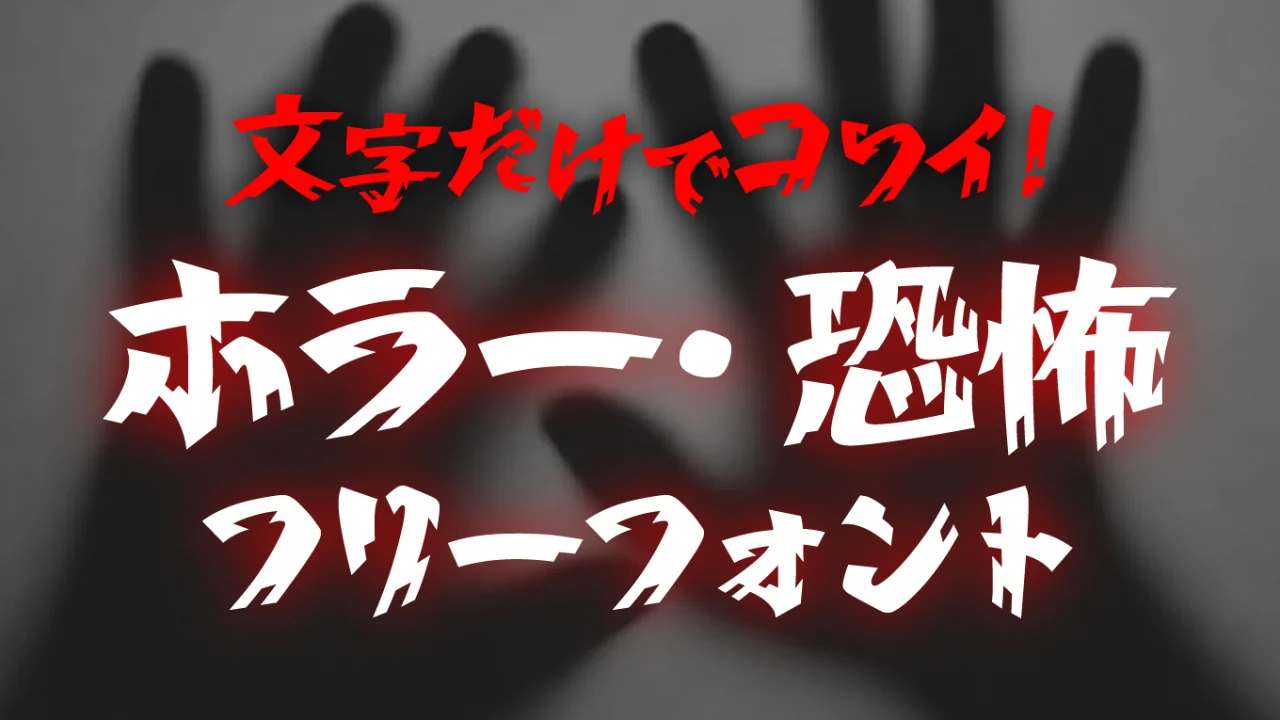
デザインでホラーや恐怖、オカルト、不気味さ、悪人らしさ、精神的な動揺や疲労感などを表現したいとき、フォントの印象で文字を選ぶ場面は意外と多いものです。文字は情報を伝えるだけでなく、見る人に感情や空気感を伝える大切なデザイン要素でもあります。
同じ言葉でも、フォントが変わるだけで「不気味さ」や「狂気」「不安感」「違和感」といった印象は大きく変化します。かすれた文字や歪んだ文字、崩れたような字形などを使うことで、視覚的に強いインパクトを与えることもできます。
今回は、ホラー・恐怖・オカルト系の演出にぴったりな日本語フリーフォントをご紹介します。恐怖演出はもちろん、悪役のセリフ、サスペンス作品、疲労感や混乱状態を表現したい場面、動画のテロップやアイキャッチなどにも活用できます。
文字だけでも十分に“怖い”。そんなインパクト抜群のホラー・恐怖系フリーフォントをぜひチェックしてみてください。今回は「不気味・不穏・サイコ」「和風ホラー・怪談」「お化け屋敷・ゾンビホラー」といったカテゴリごとにご紹介します。
ホラー・恐怖系のフリーフォントのまとめ
以下のサンプル画像は、本記事で紹介しているフォントの一部です。かすれや歪み、不規則な輪郭、崩れた字形など、それぞれ異なるアプローチで“恐怖”や“不気味さ”を表現しており、文字だけでも強いホラー感が伝わるデザインとなっています。
ホラー作品やオカルト系デザインはもちろん、不安感や狂気、違和感を演出したい場面でも活躍するフォントばかりなので、ぜひデザイン制作やアイキャッチ、動画テロップなどに取り入れてみてください。
不気味・不穏・サイコにおすすめホラーフォント
じわじわと不安を煽るような演出や、どこか異常さを感じさせるデザインを作りたいときは、フォント選びがとても重要です。文字の歪みや不揃いさ、独特な違和感をもつフォントを使うことで、サイコホラーや不気味な世界観をよりリアルに表現できます。まずは、不穏さや狂気を感じさせるホラーフォントを紹介します。
コミック古印体
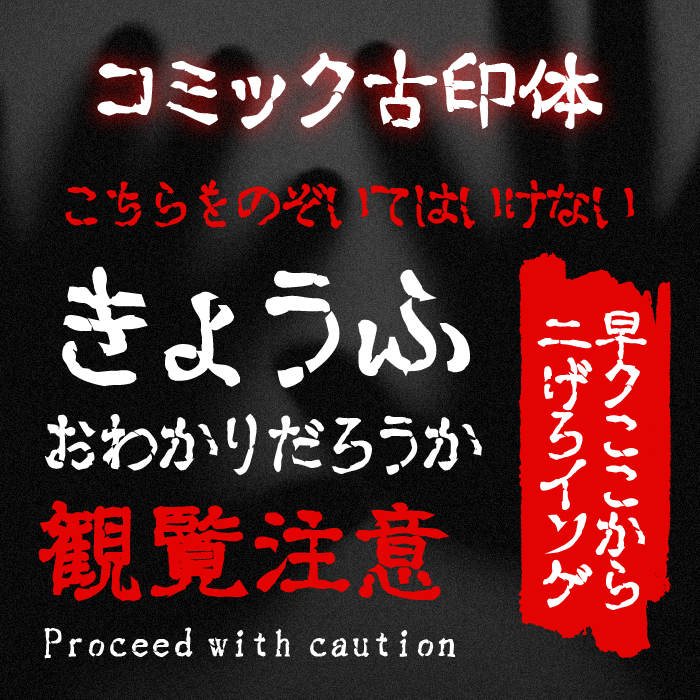
| ホラー・恐怖度 | ★★★★★ |
| おすすめのシーン | 怪談、呪いのメッセージ、警告表示、都市伝説、サスペンス演出 |
コミック古印体は、かすれた質感と不規則な線の揺らぎが特徴的なフォントです。どこか古びた印象や不安定さを感じさせるデザインで、文章そのものに不気味な空気感を与えられます。ホラー作品のタイトルや警告文にもぴったりなフォントです。
漫画の吹き出しやセリフなどにもぴったりです。
イバラ字
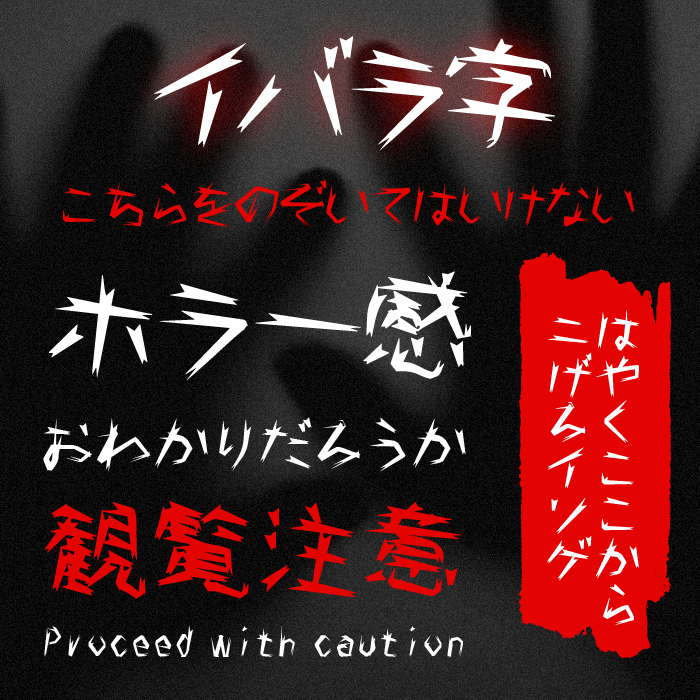
| ホラー・恐怖度 | ★★★★☆ |
| おすすめのシーン | 襲撃シーン、狂気表現、パニック演出、ホラーゲーム、危険警告 |
イバラ字は、鋭く尖ったエッジと引き裂かれたような独特の造形が印象的なフォントです。攻撃的で不安を煽るデザインになっており、視覚的に強い恐怖感や異常性を演出できます。ホラーゲームやパニック演出にも相性が良いフォントです。
異國ひらがな
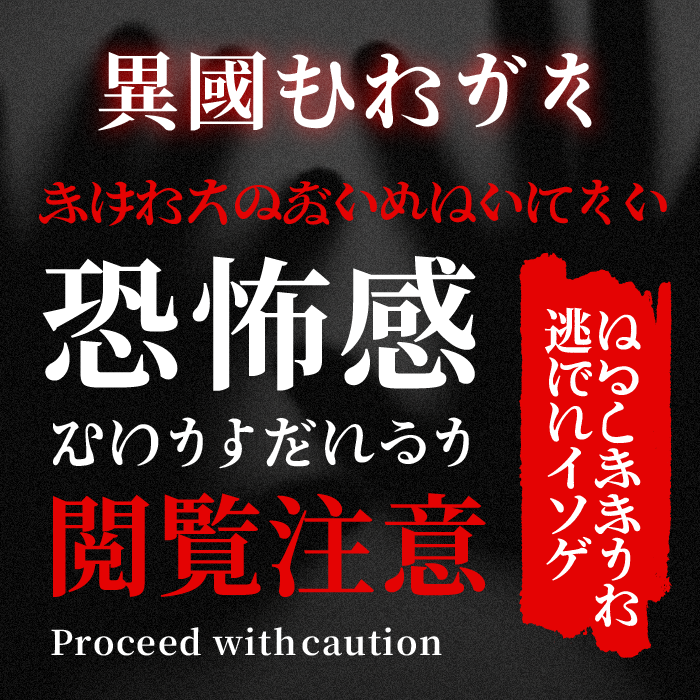
| ホラー・恐怖度 | ★★★★★ |
| おすすめのシーン | 和風ホラー、怪異の登場、静かな恐怖、不穏な演出、異界表現 |
異國ひらがなは、明朝体をベースとして、ひらがなに独特の崩しを取り入れて違和感を加えたフォントです。美しさの中に不穏さが潜んでおり、じわじわと不気味さを感じさせる表現に向いています。
ボトムズ
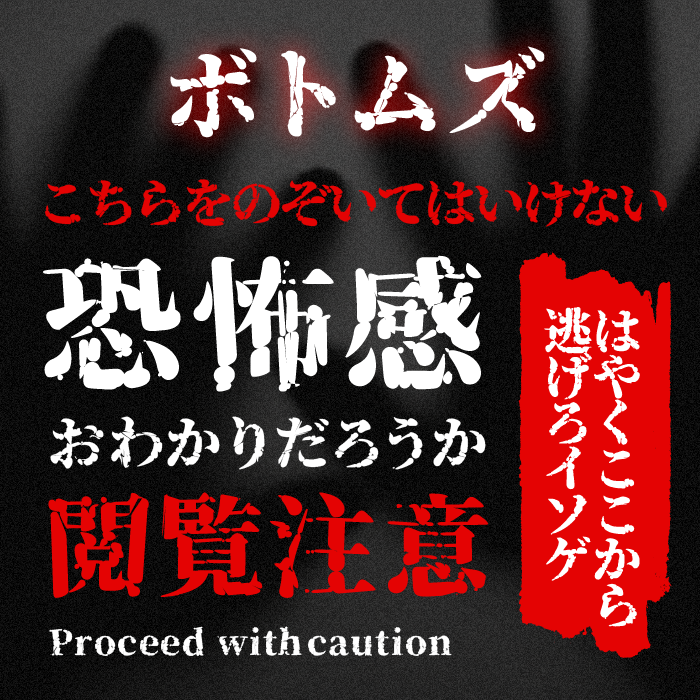
| ホラー・恐怖度 | ★★★★★ |
| おすすめのシーン | 怪談、呪いのメッセージ、警告表示、都市伝説、サスペンス演出 |
ボトムズは、源ノ明朝をベースとして、沼の底のような質感が特徴的なフォントです。血液や溶けた物質を連想させるビジュアルで、一目で異常さや不気味さを伝えられます。
異形明朝
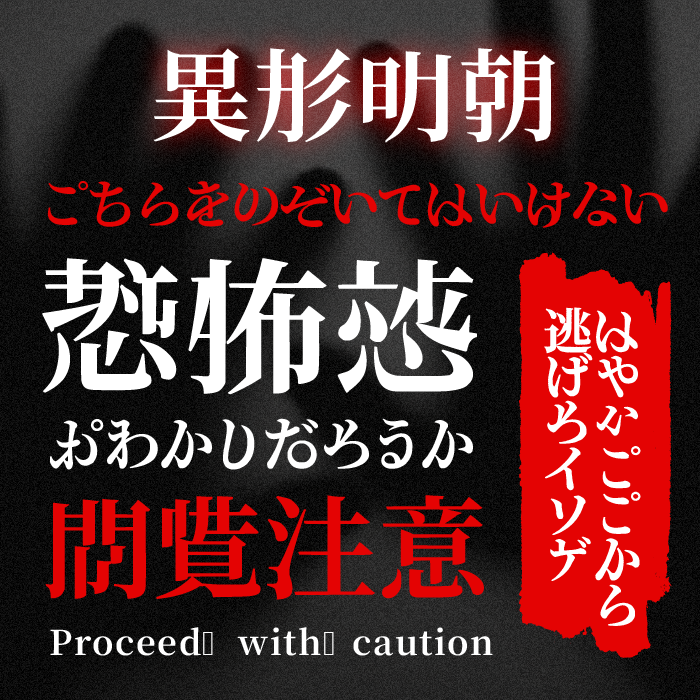
| ホラー・恐怖度 | ★★★★★ |
| おすすめのシーン | オカルト演出、怪奇現象、都市伝説、ミステリー作品、不穏なタイトル |
異形明朝は、源ノ明朝をベースに、生成AIで明朝体のチューニングして生成された不気味なフォントです。整った印象の中に潜む異常性が特徴で、静かでじわじわと迫る恐怖演出に向いています。オカルト作品とも相性が良いフォントです。
おそろしげ明朝
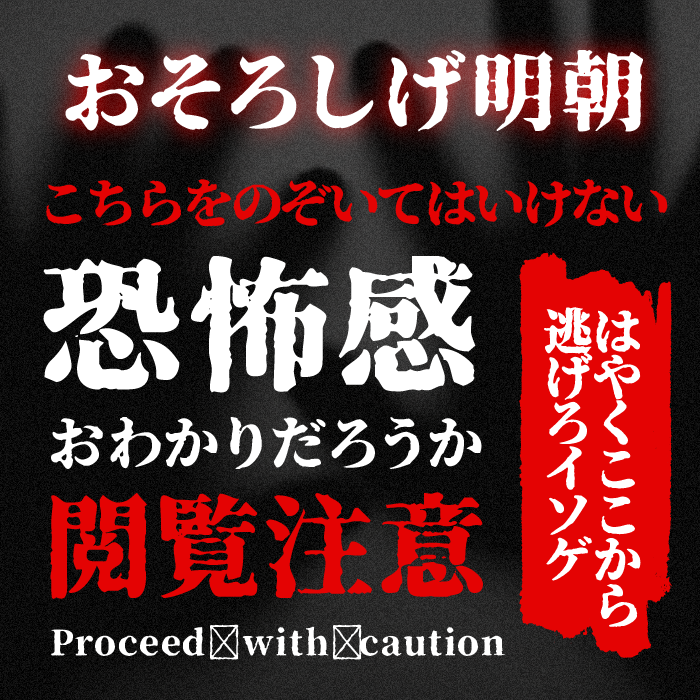
| ホラー・恐怖度 | ★★★★★ |
| おすすめのシーン | 怪談演出、古文書表現、心霊現象、ホラー映画風デザイン、呪術表現 |
おそろしげ明朝は、文字の輪郭が削れたような荒れた質感が特徴的な明朝体フォントです。古びた資料や封印された文書のような雰囲気を演出しやすく、王道のホラー演出にぴったりです。恐怖感をじっくり伝えたい場面に向いています。
ダイニングメッセージ
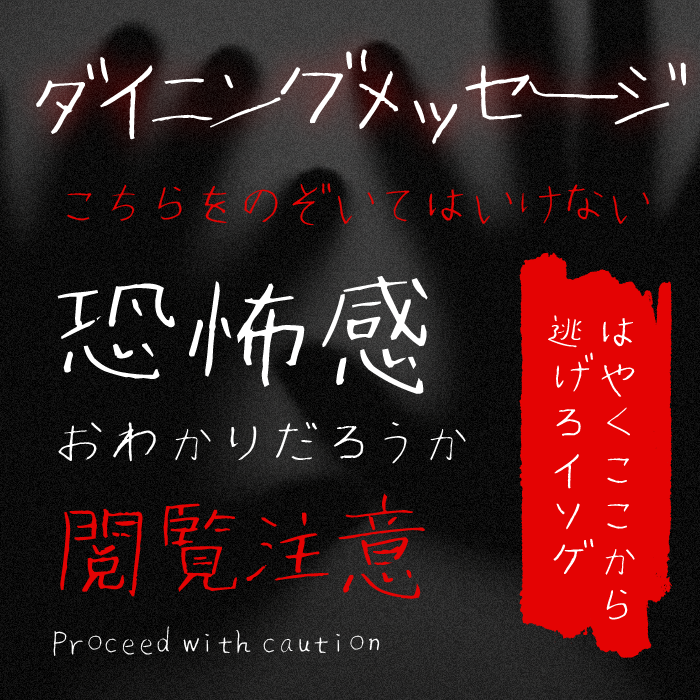
| ホラー・恐怖度 | ★★★☆☆ |
| おすすめのシーン | 怪談、呪いのメッセージ、警告表示、都市伝説、サスペンス演出 |
ダイニングメッセージは、手書きのような不安定さと細い線の揺らぎが特徴のフォントです。犯人が残したメモや精神的に不安定な人物の書き込みのようなリアルな怖さを演出できます。サイコホラー作品で特に活躍するフォントです。
SY気もミン
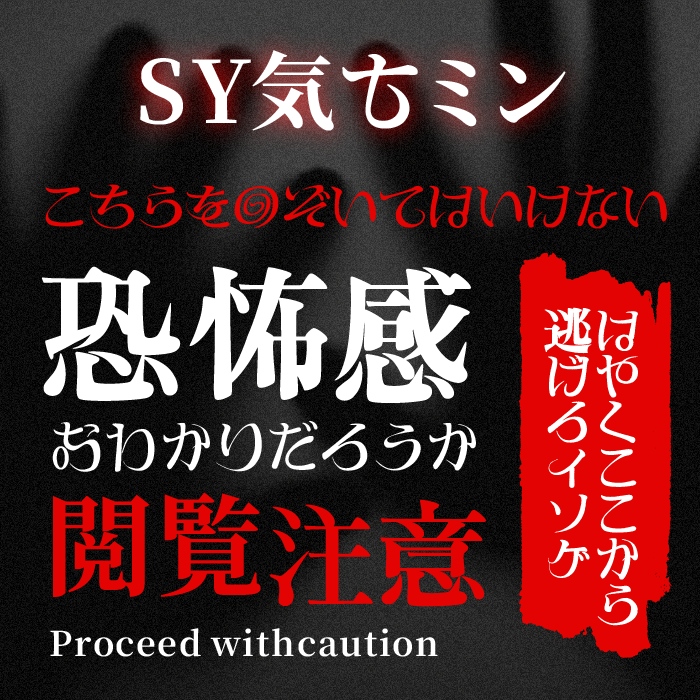
| ホラー・恐怖度 | ★★★★★ |
| おすすめのシーン | 心理ホラー、静かな恐怖、不穏な演出、都市伝説、ミステリー作品 |
SY気もミンは、明朝体をベースにしながら文字の一部が歪んでいたり、崩れていたり、気味悪い雰囲気フォントです。一見すると普通に見えながらも、どこか不安になる絶妙なデザインが特徴です。静かな恐怖や心理的な不気味さを表現したい場面に向いています。
チカラヅヨク
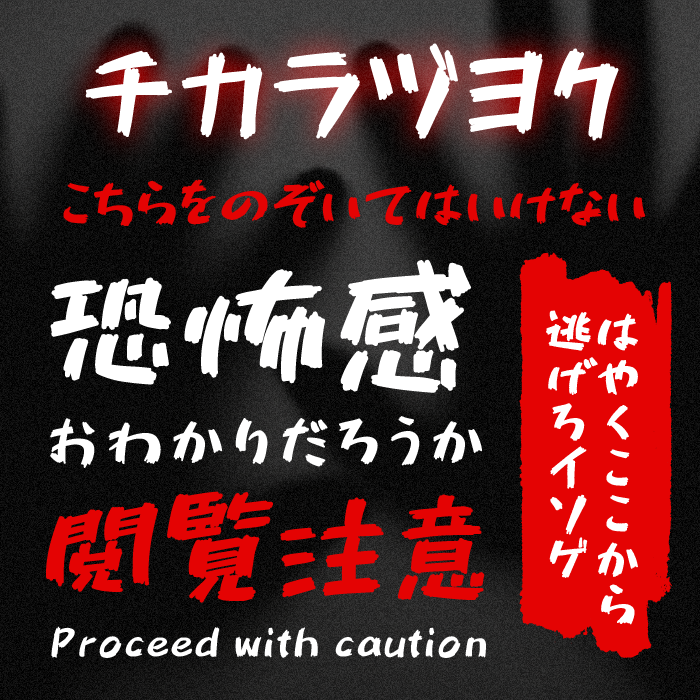
| ホラー・恐怖度 | ★★☆☆☆ |
| おすすめのシーン | 怪談、呪いのメッセージ、警告表示、都市伝説、サスペンス演出 |
チカラヅヨクは、荒々しく勢いのある筆致が特徴的な力強いフォントです。通常はエネルギッシュな表現に使われますが、赤文字やノイズ演出と組み合わせることで異常な迫力や恐怖感を強く伝えられます。緊迫感を高めたい場面におすすめです。
チカラヨワク
| ホラー・恐怖度 | ★★☆☆☆ |
| おすすめのシーン | 心理ホラー、不安を煽る演出、怪異のささやき、不穏な会話、静かな恐怖 |
チカラヨワクは、力が抜けたような柔らかく不安定な線が特徴的なフォントです。通常は脱力感のある表現向けですが、ホラー表現では精神的な不安や不気味な違和感を演出できます。静かに怖さを伝えたい場面と相性の良いフォントです。
鉄瓶ゴシック
| ホラー・恐怖度 | ★★★★★ |
| おすすめのシーン | 警告画面、異常事態の演出、ホラーゲーム、怪異出現、不穏なタイトル |
鉄瓶ゴシックは、どっしりとした太さとわずかに歪んだ輪郭が特徴的なゴシック体フォントです。重厚感のあるデザインが圧迫感や異常な存在感を演出しやすく、視覚的にじわじわと恐怖を伝えられます。警告表示やインパクトの強いホラー演出にぴったりなフォントです。
コミックホラー恐怖
| ホラー・恐怖度 | ★★★★★ |
| おすすめのシーン | ホラー漫画、怪談演出、閲覧注意表示、恐怖タイトル、心霊コンテンツ |
コミックホラー恐怖は、文字の輪郭が崩れたような不安定さを持つホラー特化型フォントです。読むだけで違和感を覚える独特なデザインが特徴で、王道の恐怖演出を強く支えてくれます。タイトルから警告文まで幅広く使いやすいフォントです。
百鬼夜行
| ホラー・恐怖度 | ★★★★★ |
| おすすめのシーン | 妖怪作品、和風ホラー、怪異出現、怪談タイトル、異世界演出 |
百鬼夜行は、角ばった独特な造形と和風ホラーらしい力強さが印象的なフォントです。妖怪や怪異を連想させる独自の存在感があり、一目で異世界感や異常さを演出できます。和風ホラー作品では特に映えるフォントです。
ふぉんとうは怖い明朝体
| ホラー・恐怖度 | ★★★★★ |
| おすすめのシーン | サイコホラー、不穏な手紙、怪奇現象、オカルト演出、静かな恐怖 |
ふぉんとうは怖い明朝体は、明朝体らしい上品さを残しながらも細部に不気味な違和感を加えたフォントです。整ったデザインなのにどこか不安を感じさせる絶妙なバランスが魅力で、静かに迫る恐怖を表現したい場面に向いています。
京華老宋体
| ホラー・恐怖度 | ★★★★☆ |
| おすすめのシーン | 古文書演出、和風怪談、伝承ホラー、呪術表現、歴史ミステリー |
京華老宋体は、クラシカルな明朝体をベースにした独特なレトロ感のあるフォントです。古い文献や封印された記録のような雰囲気があり、古典的な怪談や歴史系ホラーとの相性が抜群です。静かで格式ある恐怖演出におすすめです。
和風ホラー・怪談におすすめホラーフォント
日本ならではの怪談や呪い、古びた因習のような空気感を表現するなら、和の雰囲気を感じさせるフォントがおすすめです。筆文字やかすれ表現、古風な質感をもつフォントを取り入れることで、一気に和風ホラーらしい独特の怖さを演出できます。ここでは、怪談や和風ホラー作品にぴったりなフォントをまとめました。
異世明
メルティスクラッチ
| ホラー・恐怖度 | ★★★★☆ |
| おすすめのシーン | 血文字演出、ゾンビ感染表現、スライム状クリーチャー、バイオホラー、異常警告表示 |
メルティスクラッチは、文字が溶けてドロドロとした血のように見えるデザインフォントです。血液や粘液のような不快感をそのまま文字で表現でき、ゾンビホラーや感染系作品と非常に相性が良い仕上がりになっています。
ゆずペン壊